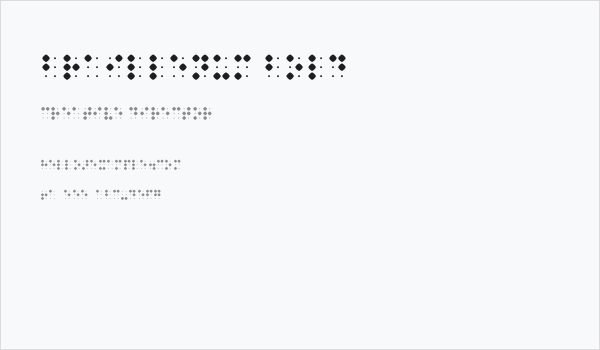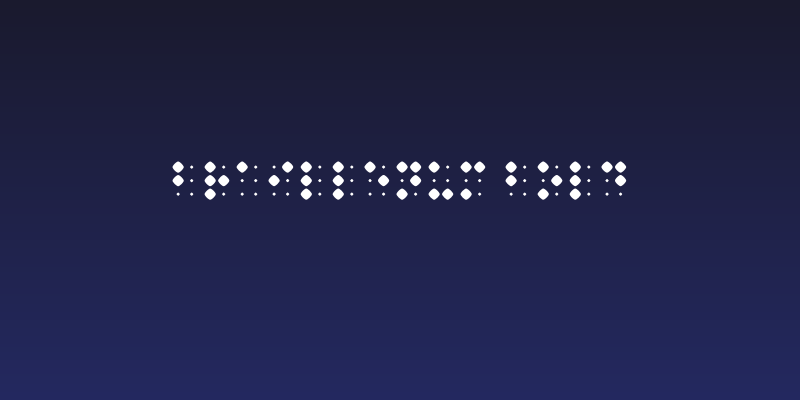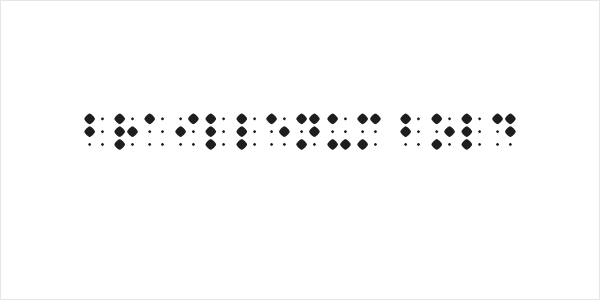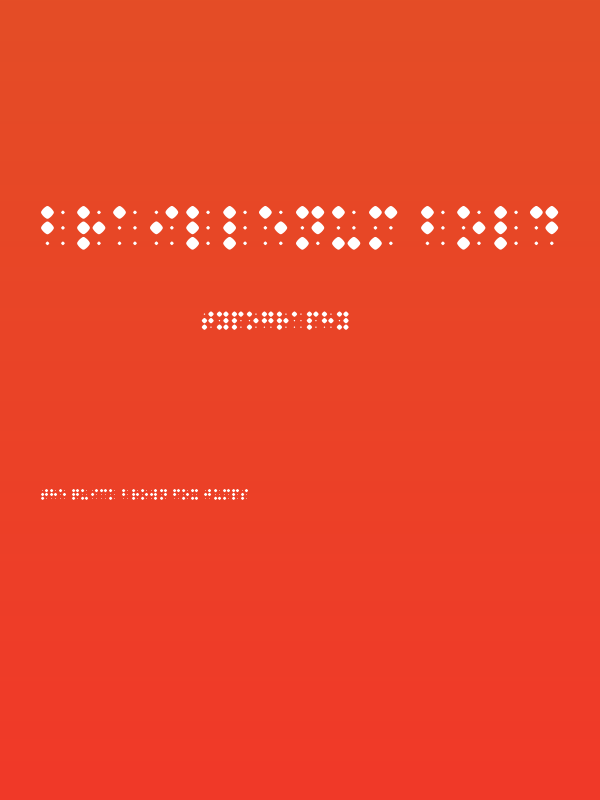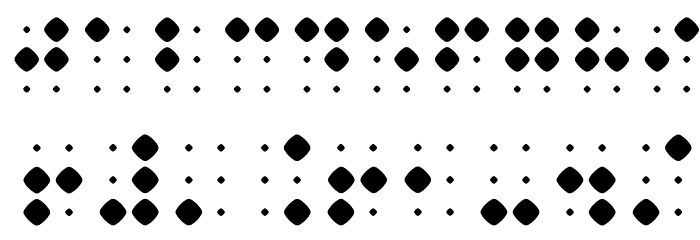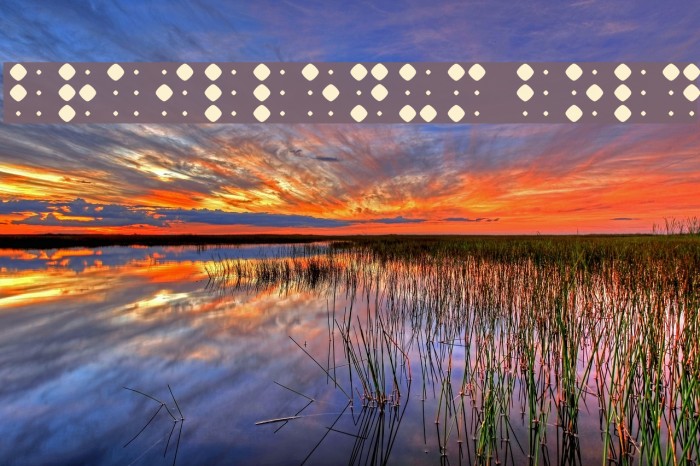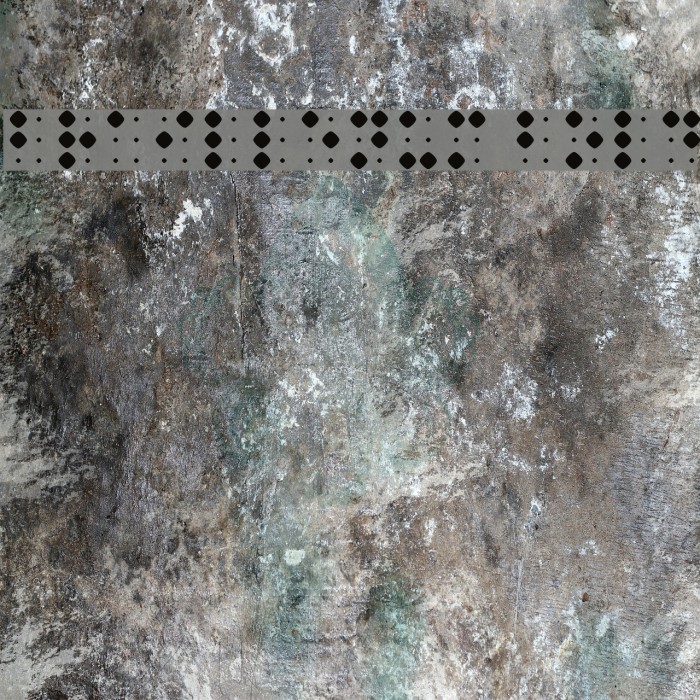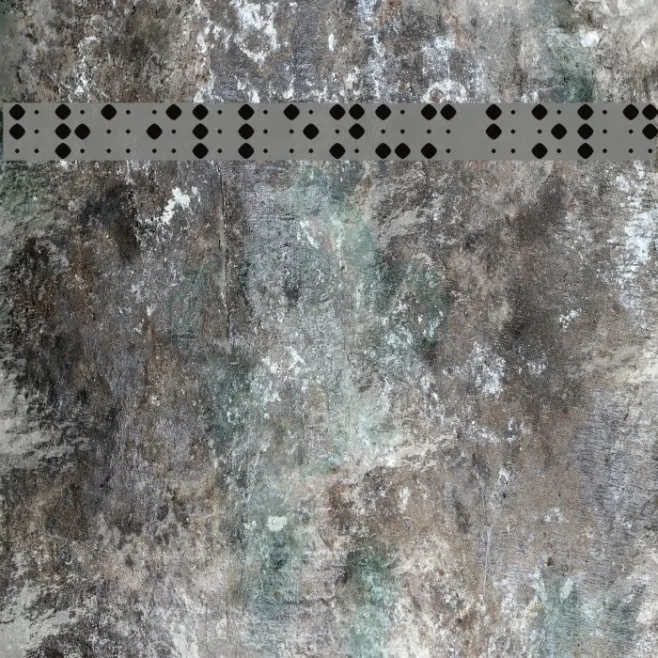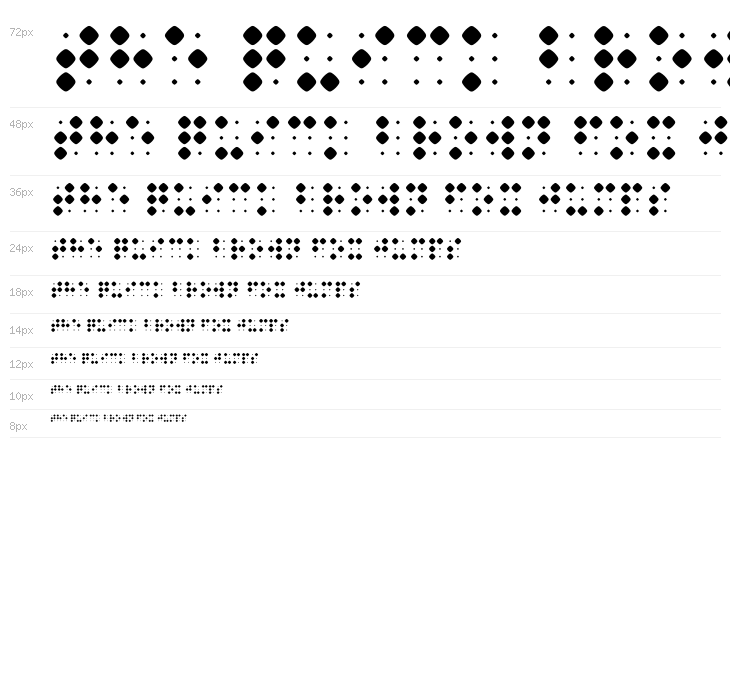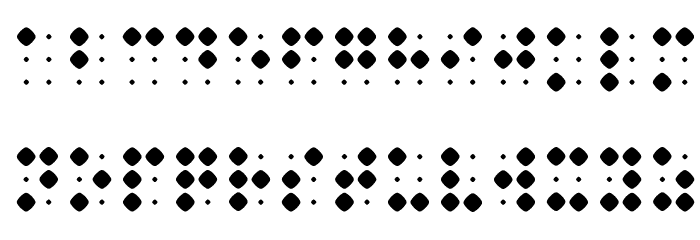
Braillenum Bold Font
| Estilo general | Functional |
| Caso de uso | Accessibility, Educational materials |
| Proyectos propuestos | This representation can be used in educational materials for teaching Braille, creating accessible signage, or designing tactile books. |